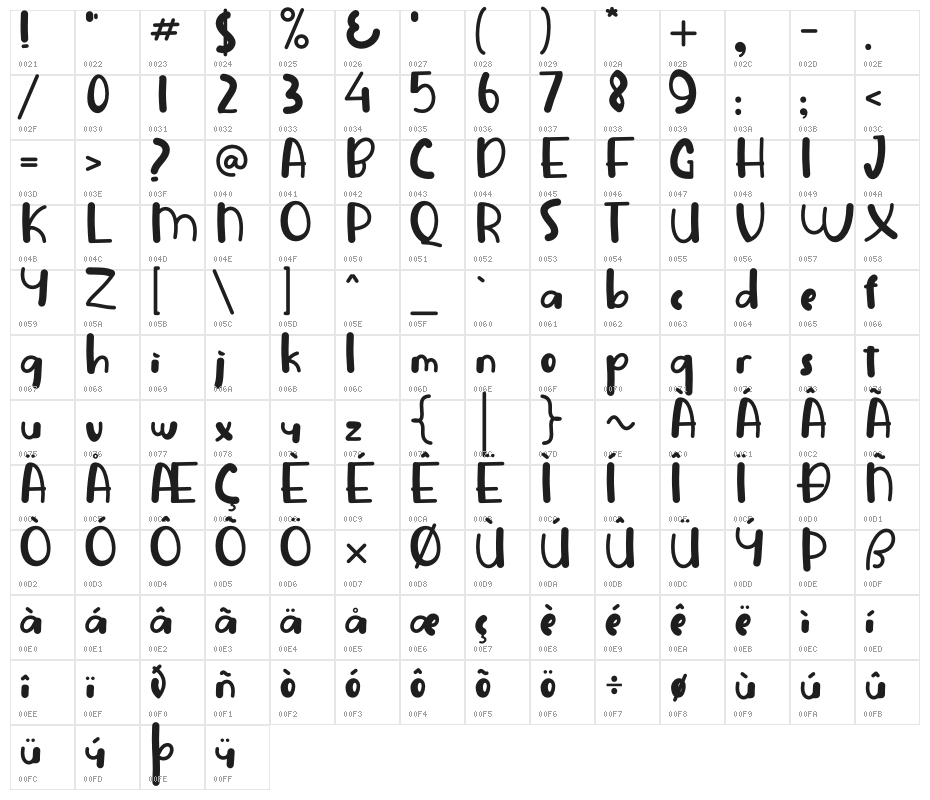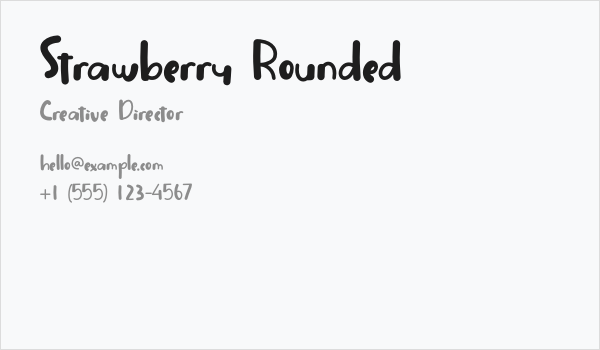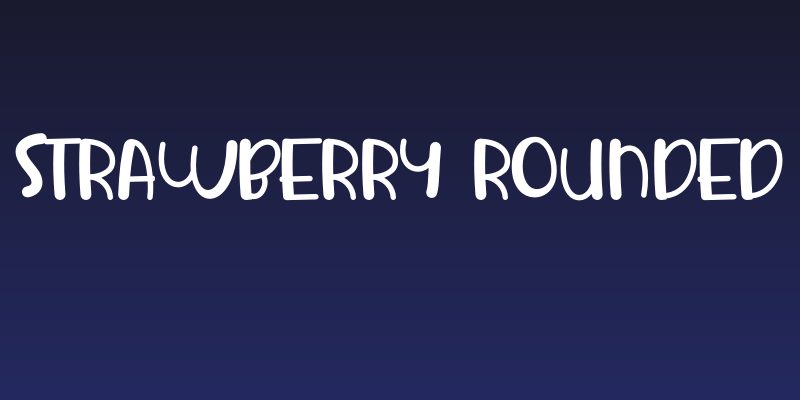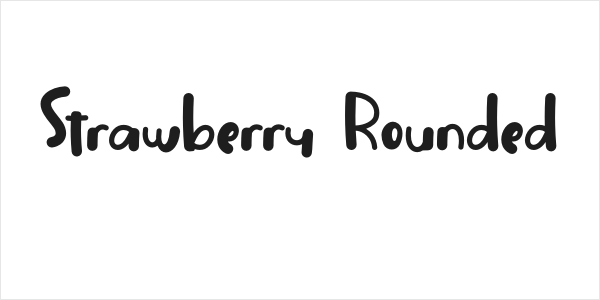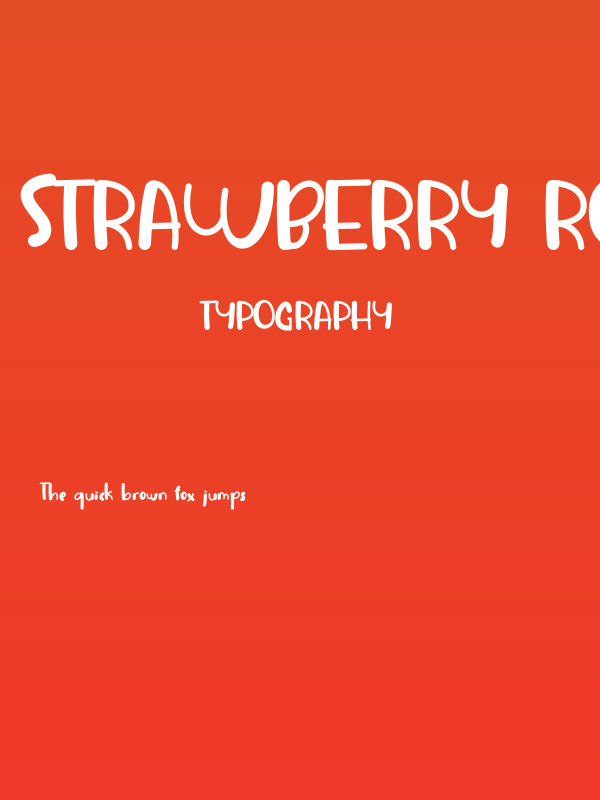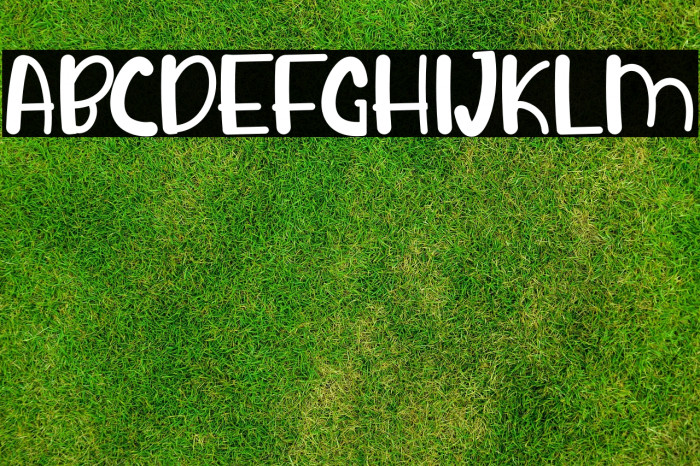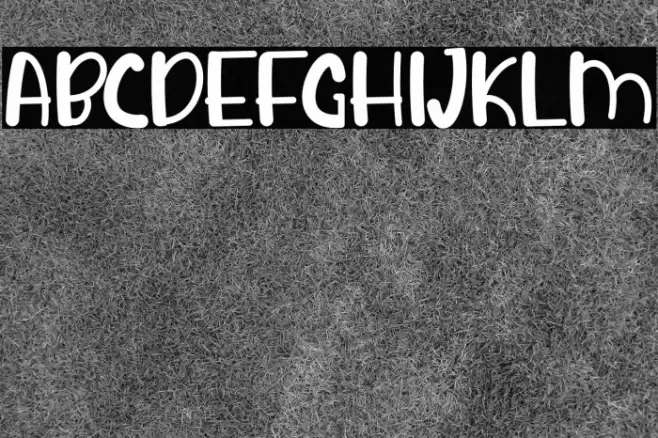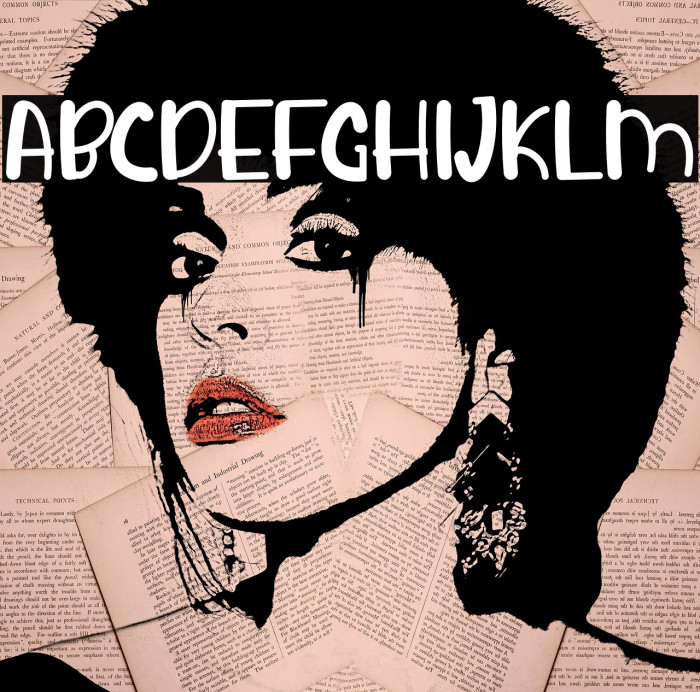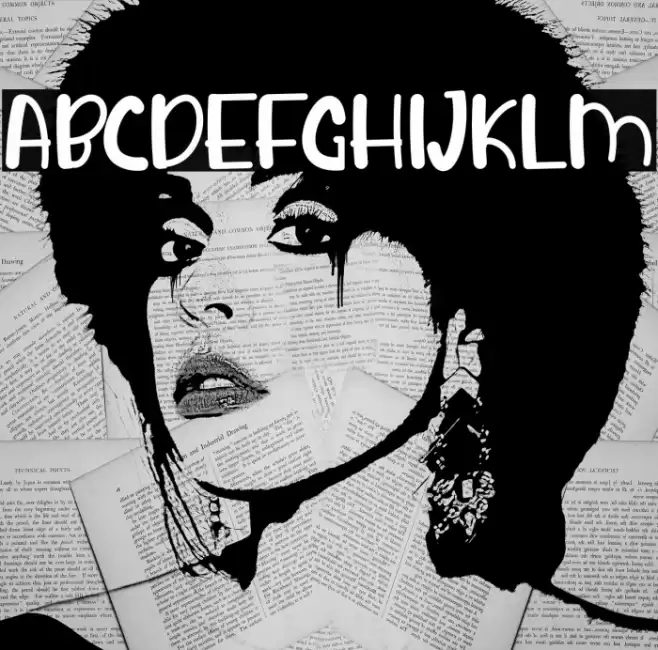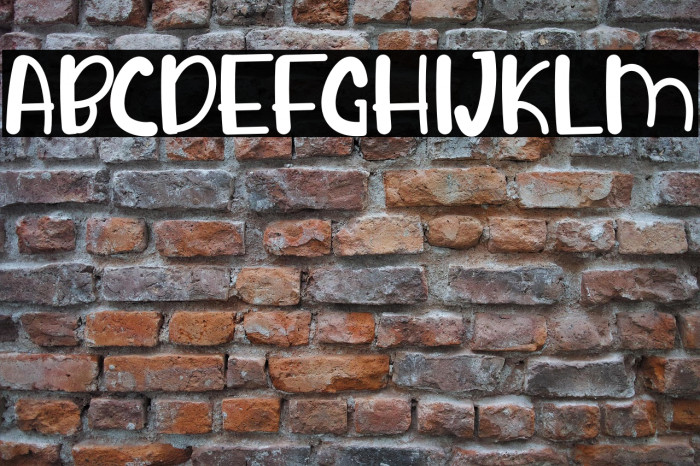
Strawberry Rounded Font
| 用途 | Headlines, Logos, Casual Text |
| おすすめプロジェクト | Ideal for children's books, playful branding, greeting cards, and casual invitations. |